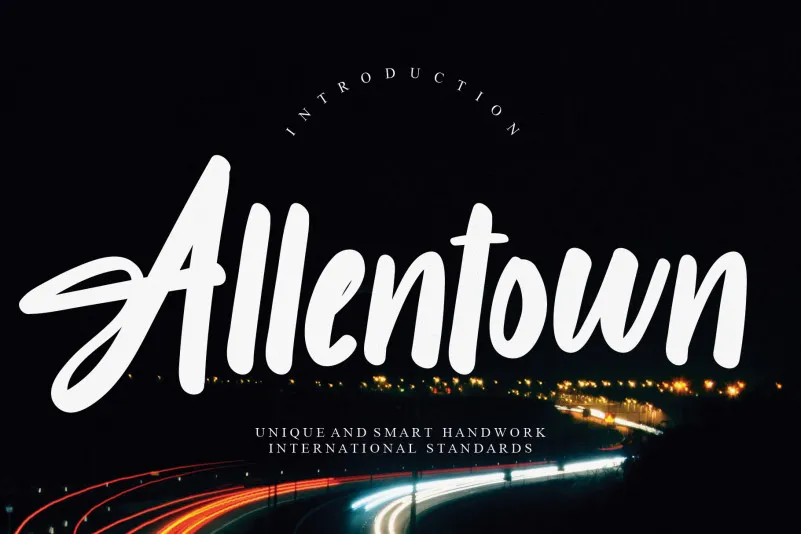
Allentown Script Font
Nossa fonte ‘Allentown Script Font’ é ideal para aqueles que buscam uma sensação envolvente e natural na sua obra final. Inspirada no estilo delicado e fluido de cenas feitas à mão, a Allentown Script oferece linhas suaves e curvas sutis que se mesclam perfeitamente com seu design único. Esta fonte é um convite para expressar suas ideias de uma forma elegante e pessoal. Ela foi projetada pelo designer creativeletter e traz um toque especial, dando a cada palavra ou título o brilho necessário para destacá-los em qualquer projeto. Seja para criar cartazes memoráveis, designs de site profissionais ou até mesmo ilustrações criativas, a Allentown Script proporciona uma experiência extraordinária. Ao trabalhar com ela, você mergulha no mundo da arte gráfica e descobre um novo nível de expressividade na sua comunicação visual. Com seu design sofisticado, é perfeita para transmitir mensagens poderosas e emocionantes através do tipo. Não importa o que esteja criando, a Allentown Script oferece uma maneira excepcional de expressar suas ideias de forma única.